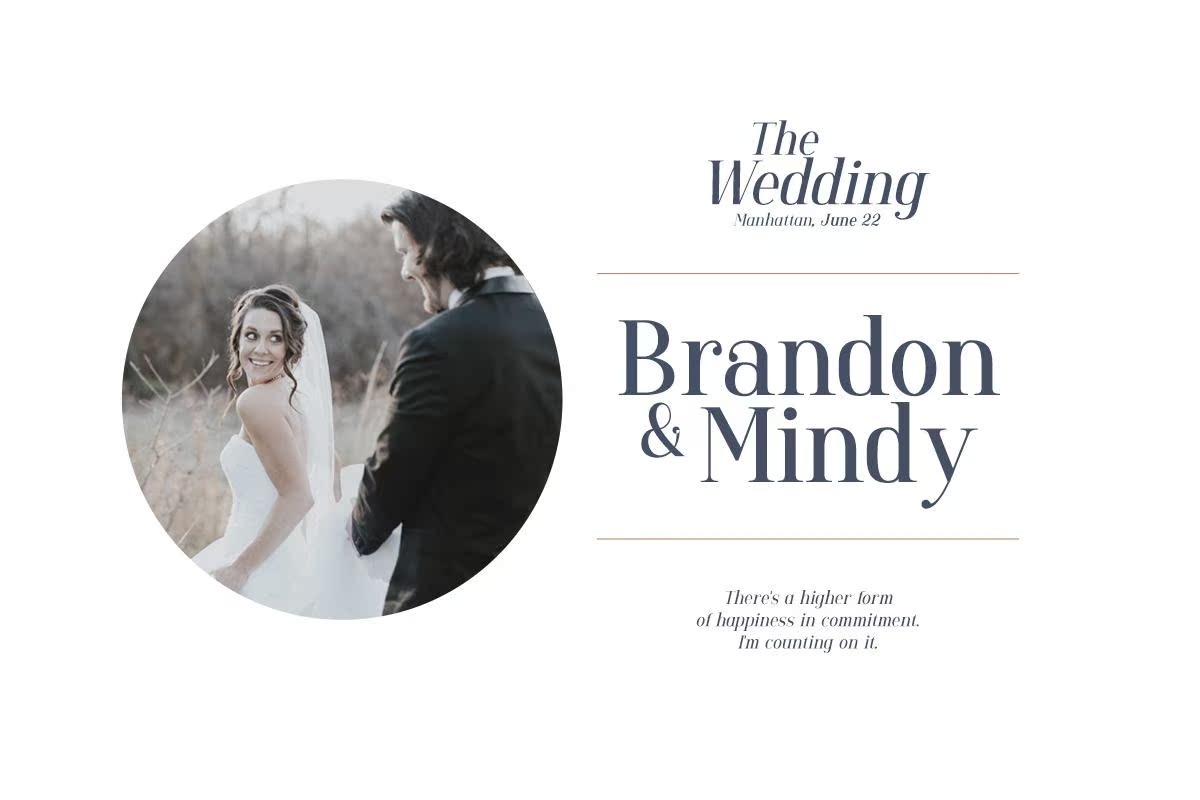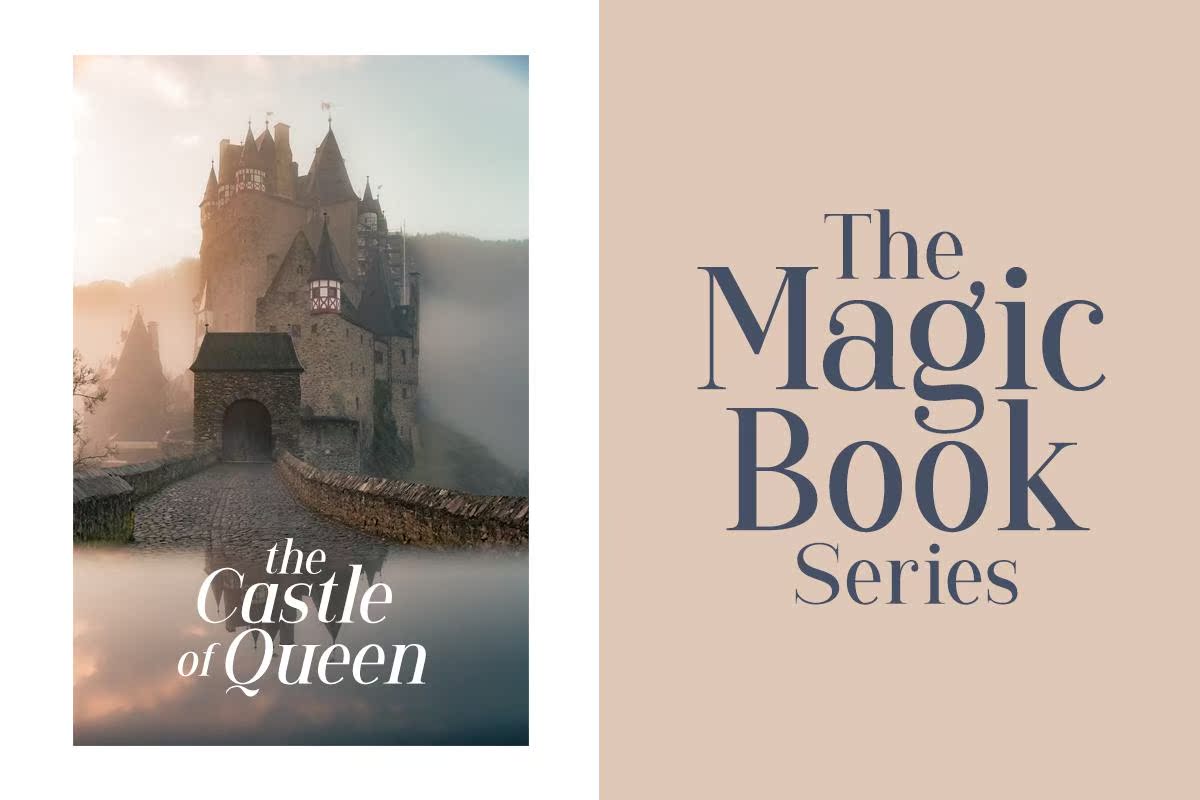
Gorgone.aversatileserift带来了丰富的体验。Gorgon非常适合那些需要字体的人,如标题、标识、服装、邀请、品牌、包装、广告等。该字体包括大写、小写、标点符号、符号和数字、样式设置、替换、连字、,EtcalSo支持多语言和ReadyPuaEncoded.Gorgone.AversatileSerift,可带来奢华的感觉。Gorgon适用于需要字体的用户,如标题、标识、服装、邀请、品牌、包装、广告等。该字体包括大写、小写、标点符号、符号和数字、文体设置、替换、连字、,ETCALSO支持多语言和alreadypuaencoded。